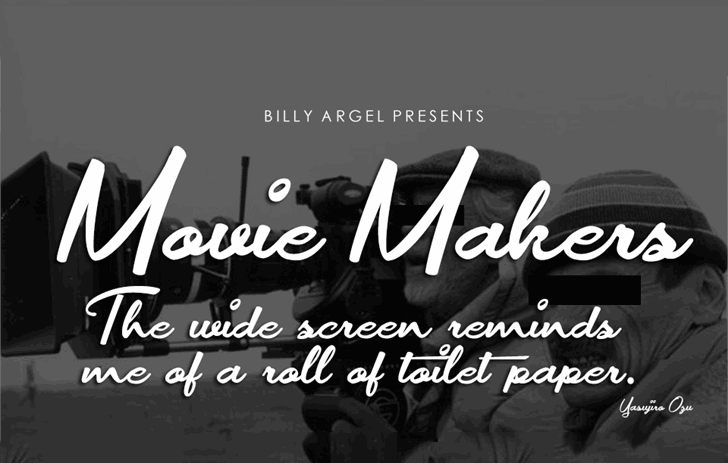
Aqui está uma descrição em português para a página de download da fonte ‘Movie Makers Font’ na categoria de Script Fonts: Estamos muito felizes por apresentar a fonte Movie Makers Font, criada pelo talentoso designer Billy Argel. Esta fonte é especialmente perfeita para quem busca um estilo elegante e distinto para projetos como trailers ou cartazes de cinema. Com uma versão parcial disponível gratuitamente para uso pessoal, o designer também oferece opções comerciais e completas através do seu site www.billyargel.com. Para mais informações sobre as licenças disponíveis, os interessados podem entrar em contato com Billy Argel através de email. Tecnicamente uma fonte Script, a Movie Makers Font é uma escolha perfeita para aqueles que desejam adicionar um toque especial e sofisticado aos seus projetos gráficos. Com seu design fluido e delicadamente curvilíneo, esta fonte oferece uma variedade de opções para criar layouts intrigantes ou texturas interessantes. Se você é designer de gráficos ou criativo que deseja aprimorar suas habilidades digitais, o uso desta fonte pode ser um recurso valioso. Sem dúvida, ela ajudará a trazer um novo nível de profissionalismo e originalidade a seus projetos. Visite agora o site oficial do designer para mais detalhes sobre esta fonte maravilhosa e versátil.